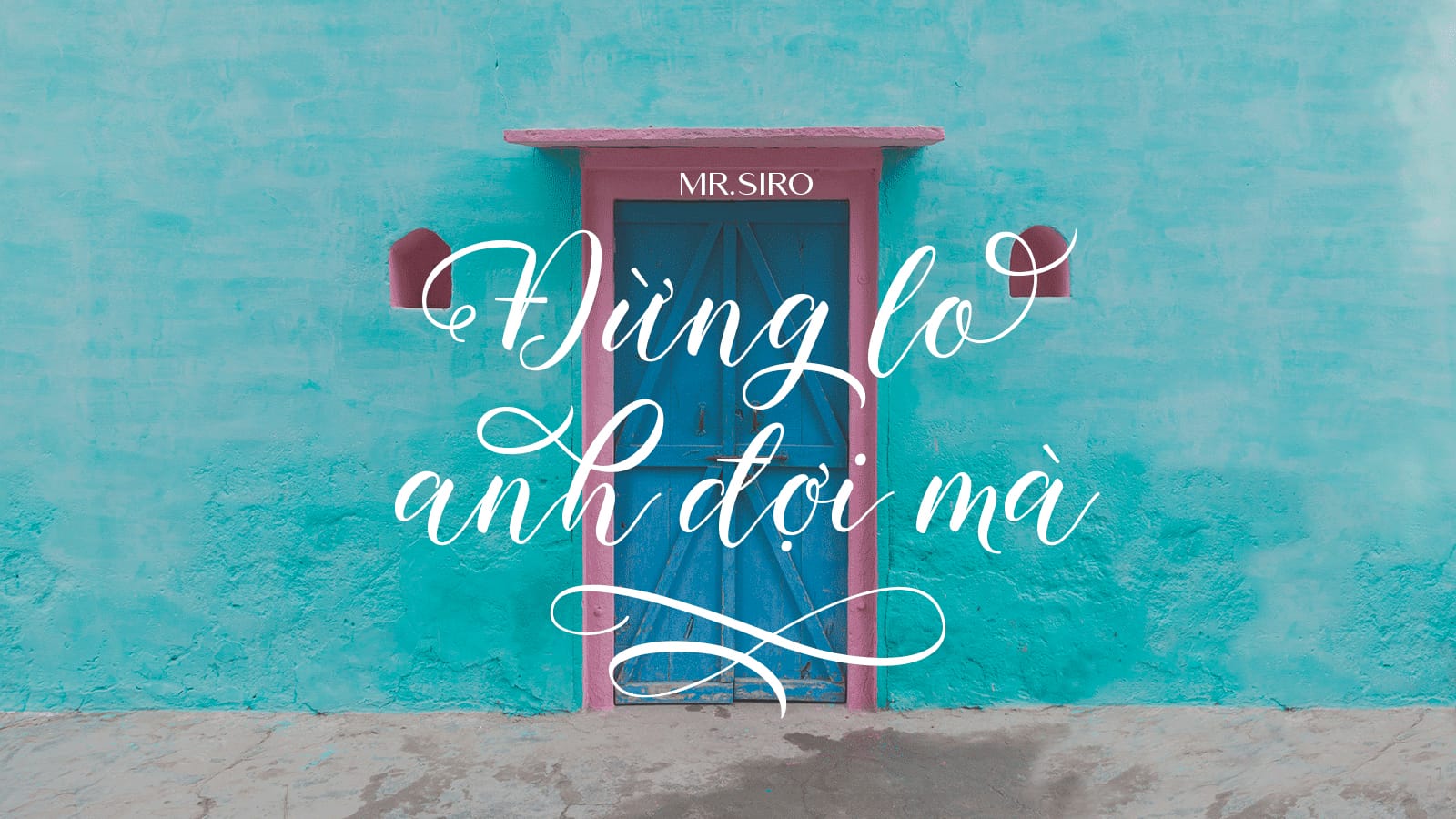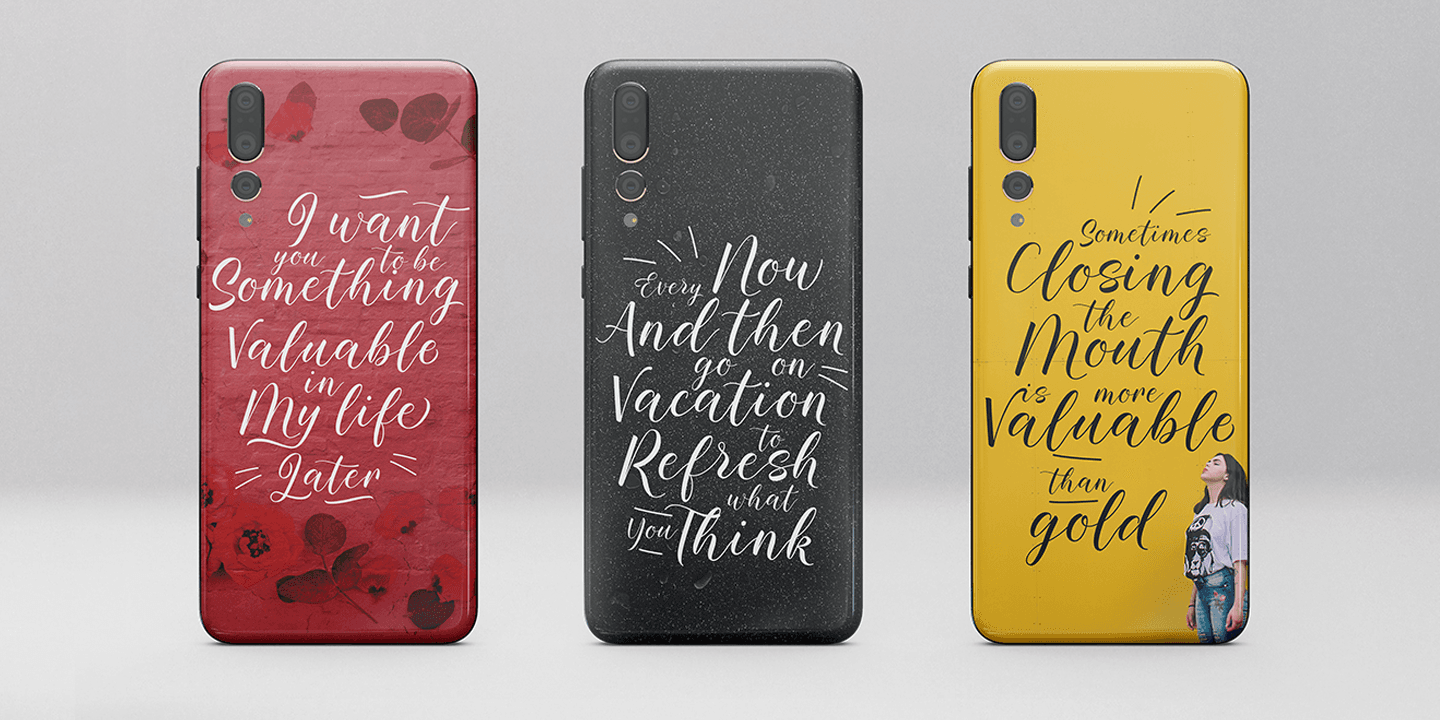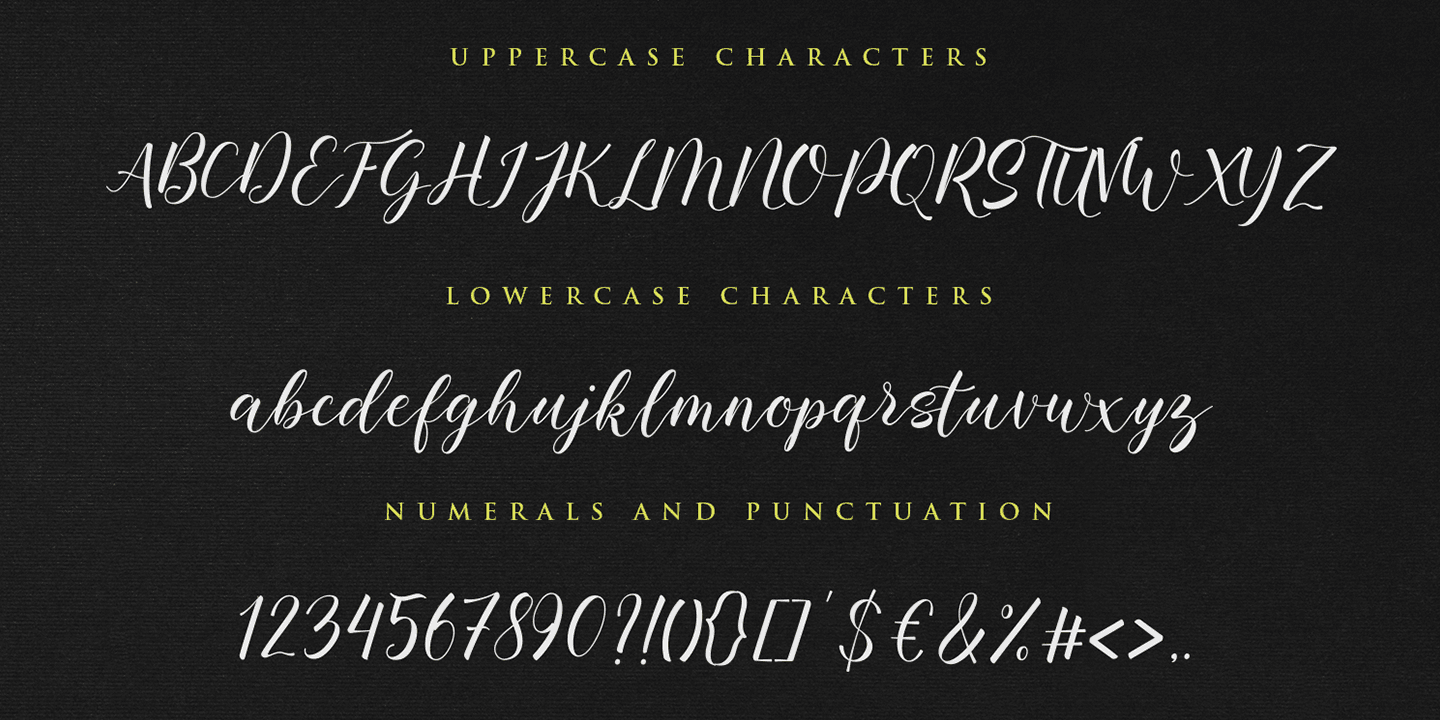
Font Baelish Việt hóa (+Swash) – Script Font
Giới thiệu font Baelish Script! một font chữ sáng tạo và thân thiện giúp bạn tạo ra nhiều thiết kế kiểu chữ đẹp phù hợp cho nhiều thiết kế của bạn.
Phù hợp cho các thiết kế thiệp chúc mừng, nhãn, trích dẫn, áp phích, lịch treo tường, typography, qoute, xây dựng thương hiệu, bao bì, trang web và rất nhiều thiết kế khác.
Baelish Script đặc biệt ở chỗ nó có vô vàn ký tự alternate cho bạn chọn cũng như tùy chọn Standard Ligatures – cho phép bạn thỏa sức thiết kế tạo ra những tác phẩm độc đáo. Đừng quên thêm Swash vào thiết kết mà bạn thấy phù hợp để làm cho nó hấp dẫn hơn nữa.
Các ký tự thay thế trong phông chữ này được chia thành một số tính năng của OpenType như Stylistic Alternates, Ligature và Ligature Alternates. Font Baelish việt hóa bởi iCiel.